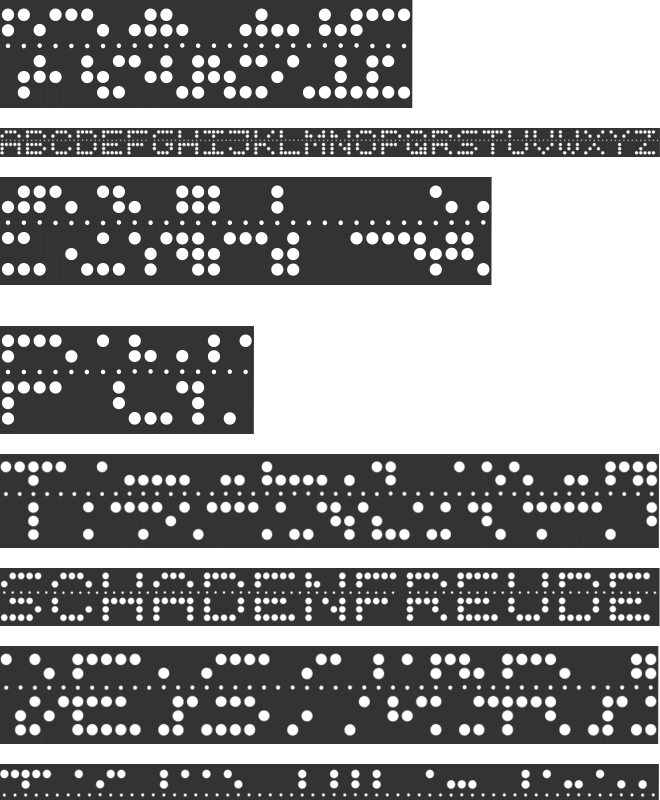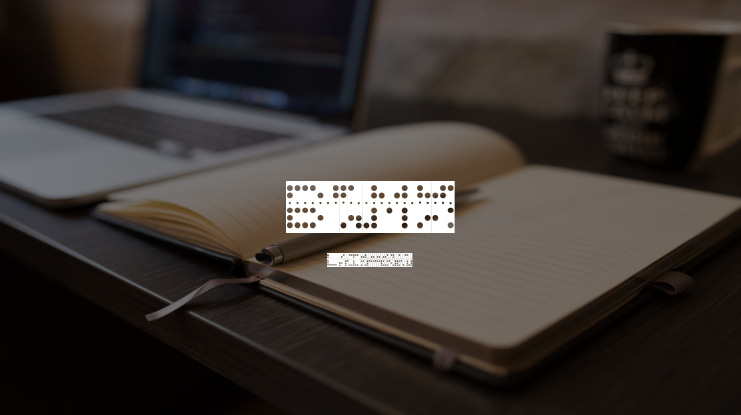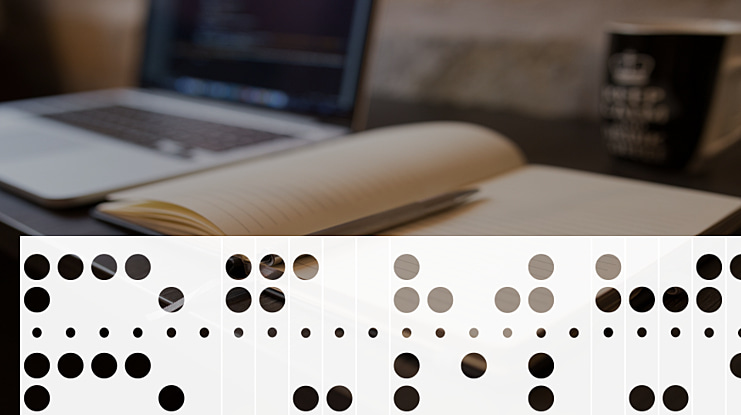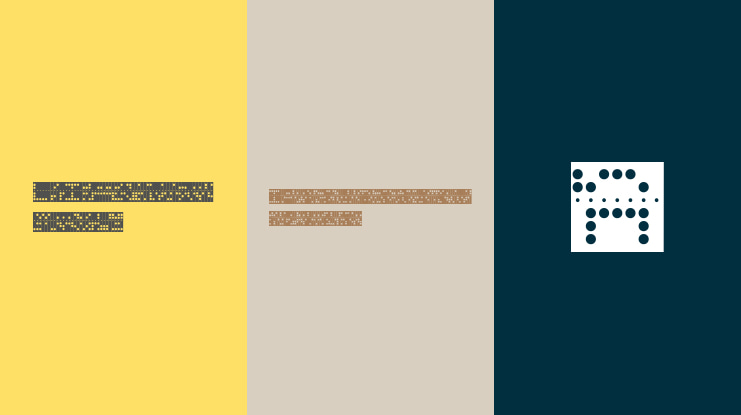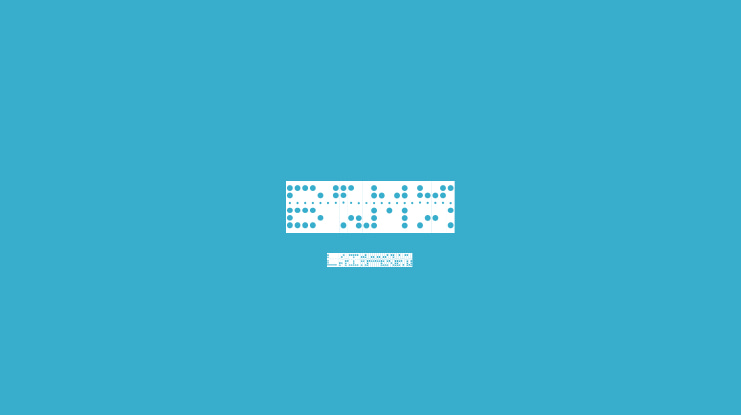
BaudotMurray Font
Peter Wiegel after Baudot Murray-Code CCITT-2
Dieser Font simmuliert Lochstreifen, sowol im Baudot Murray-Code als auch human lesbar.